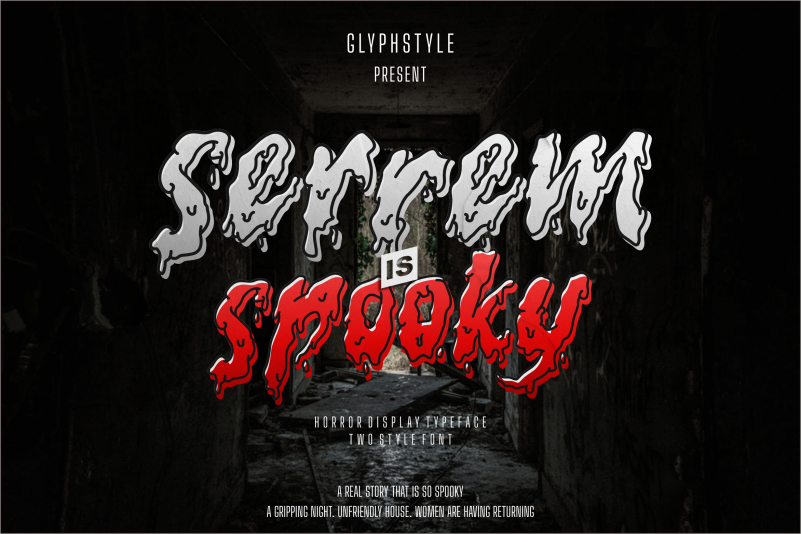
Através do seu designer GlyphStyle, Serrem Display Font é uma exuberante tipografia com influências sobrenaturais. Inspirada nas drogas sangrentas que desfilam através de filmes e quadrinhos de horror, essa font oferece duas opções: um estilo cintilante e outro mais robusto. Perfeita para as campanhas de Halloween ou projetos baseados em temas de terror, Serrem Display é uma escolha ideal. Suas formas agressivas e impressionantes podem ser usadas em diversas aplicações, incluindo a capa de um filme, logotipos de marca, postagens nas redes sociais, anúncios, cartões de convite, etiquetas para embalagens ou até mesmo as subtítulos de uma cena sobrenatural em um vídeo. Serrem Display é flexível o suficiente para atender a uma variedade de necessidades criativas e certamente será útil para qualquer projeto que exija escrita com tema de horror.